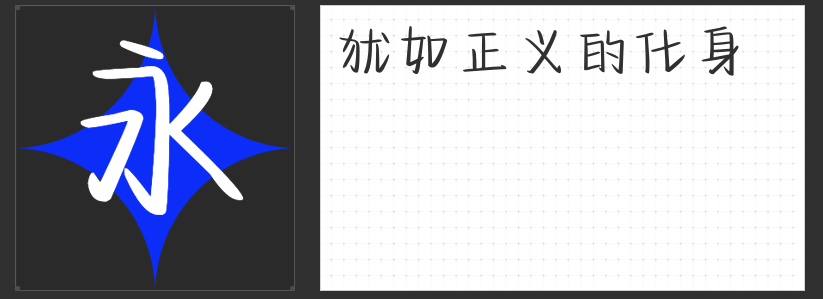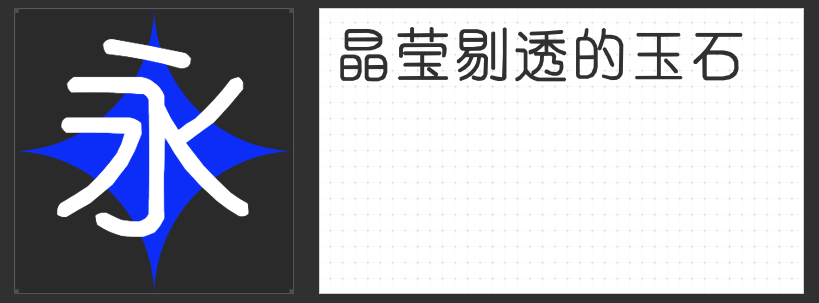
短视频视觉进阶指南:四款高辨识度商用字体的设计美学解析
在短视频内容同质化竞争激烈的当下,字体设计已成为塑造品牌调性、强化视觉记忆的关键元素。本文精选四款兼具艺术张力与实用价值的商用字体,从字形结构到性格表达,深度解析其如何为动态视觉注入独特灵魂。
一、励字磅礴简 超黑
这款突破传统黑体框架的实验性字体,以"斜正共生"的矛盾美学重构视觉平衡。左侧15°倾斜设计打破静态字形的沉闷感,右侧垂直笔画如山峦般稳固支撑,形成"横看成岭侧成峰"的空间张力。在快节奏的短视频中,其独特的字形结构既能快速抓住观众注意力,又能通过笔画粗细的微妙变化传递情绪层次,尤其适合作为标题或关键信息载体。
二、励字超级勇士简 微粗
针对数字屏幕特性优化的通用黑体,通过0.8mm外圆角处理赋予字形呼吸感。这种"刚柔并济"的设计哲学,既保持了黑体的理性秩序,又通过微曲线消解了直角带来的生硬感。在短视频场景中,其24px以上的清晰可读性与多语言适配性,使其成为字幕、标签等辅助信息的理想选择,尤其在运动镜头中仍能保持视觉稳定性。
三、字圈也字综艺弹幕体
专为弹幕场景设计的叛逆字体,以22°倾斜角度构建动态视觉语言。钝角与直角的交替出现形成独特的节奏感,配合笔画末端的锐角处理,完美复现年轻文化中"锋芒毕露"的表达态度。在短视频弹幕墙或互动设计中,其强烈的个性特征能瞬间激活观众参与感,形成沉浸式观看体验。
四、字圈也字润圆体
看似矛盾的"刚柔并济"设计哲学,在这款字体中得到诗意诠释。通过控制圆角曲率半径(R=3px),既保留了黑体的现代感,又赋予字形婴儿肌肤般的触觉联想。在短视频情感叙事中,其温暖而不失力量的视觉特质,能有效软化科技感界面,拉近与观众的情感距离。
这四款字体通过差异化的设计语言,构建起从理性到感性、从传统到先锋的完整视觉谱系。在短视频创作中,设计师可根据内容调性进行组合运用,共同打造具有记忆点的视觉系统。